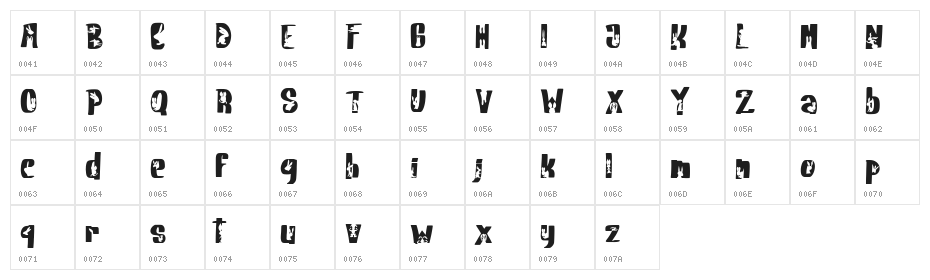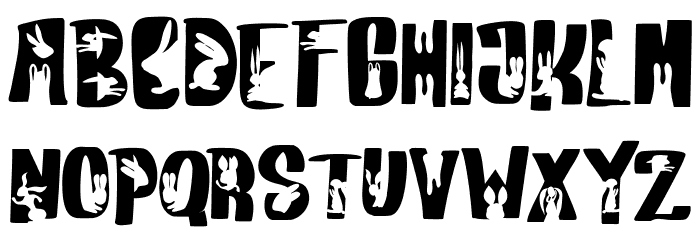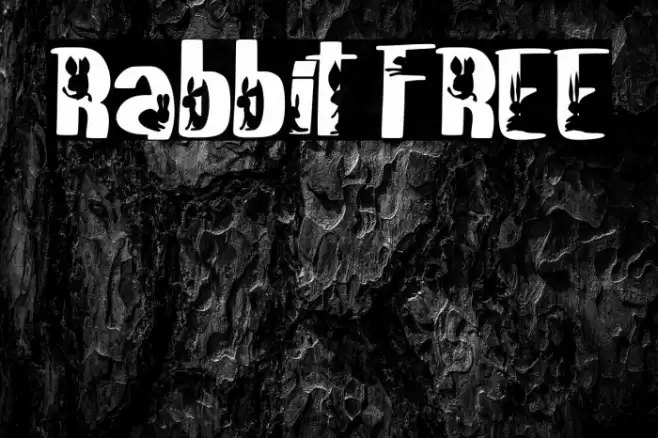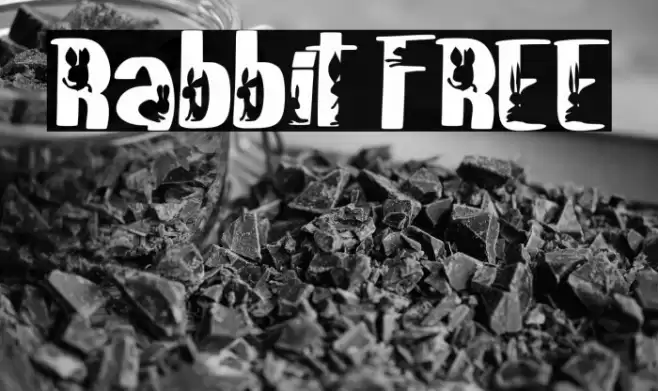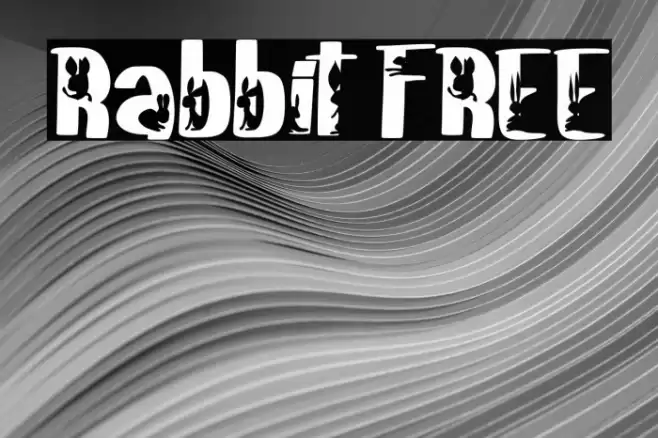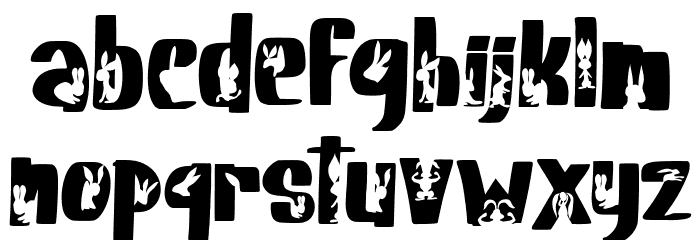
Rabbit FREE Font
| Style général | Playful, Whimsical, Decorative |
| Projets proposés | Children's books, playful branding, greeting cards, posters, and whimsical designs. |